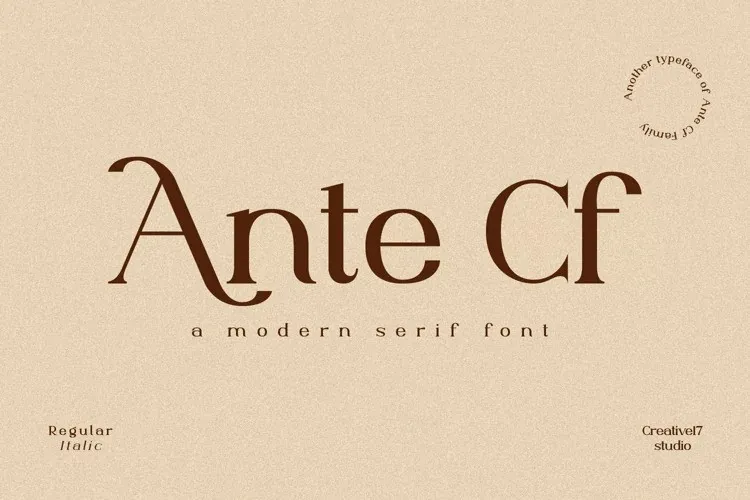
A Ante Cf Font é uma elegante serif moderna com ligaturas belas e alternativas de caracteres especiais que oferecem um grande poder para personalização. Conhecida por seu designer Irfan Hidayat, esta fonte se destaca pela sua versatilidade em diversas aplicações gráficas. Suas características multifunção a tornam perfeita para projetos que exigem sofisticação e modernidade ao mesmo tempo. Além disso, o fato de ser multilinguista também torna-a um recurso valioso para projetos internacionais ou aqueles que desejam adaptar seus design em múltiplas línguas. A Ante Cf é especialmente adequada para combinar com fontes tipográficas como script, escrita à mão e serifless minimalista em seu projeto.